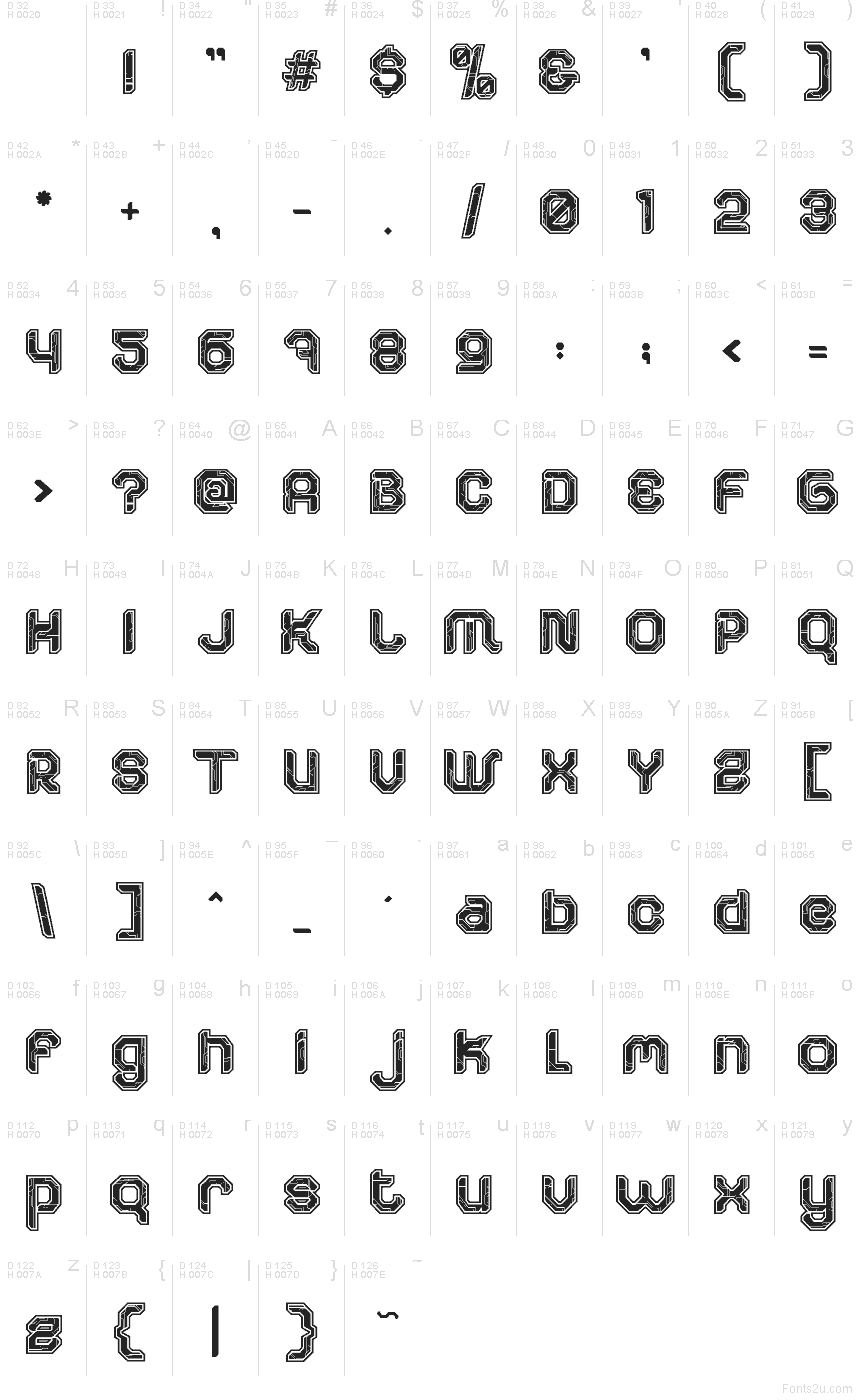
Snapshock Two
Snapshock Two od Putracetol Studio je futuristické písmo typu display, tvorené skosenými osemuholníkovými tvarmi a vkladmi, ktoré pripomínajú cesty na plošných spojoch. Toto opakujúce sa členenie dodáva písmenám strohý, inžiniersky rytmus, vďaka čomu dizajn pôsobí skôr ako kryt stroja než ako bežný technický štýl.
Najlepšie vynikne v herných tituloch, sci-fi plagátoch, e-športovom brandingu, na obaloch albumov a v nadpisoch inšpirovaných používateľským rozhraním, kde tieto segmentované vnútra ponúkajú oveľa viac než len obyčajné blokové znaky. Skvele poslúži aj pri krátkych propagačných textoch a grafike podujatí, pretože vrstvené obrysy vytvárajú technickú textúru bez potreby ďalších ilustrácií.